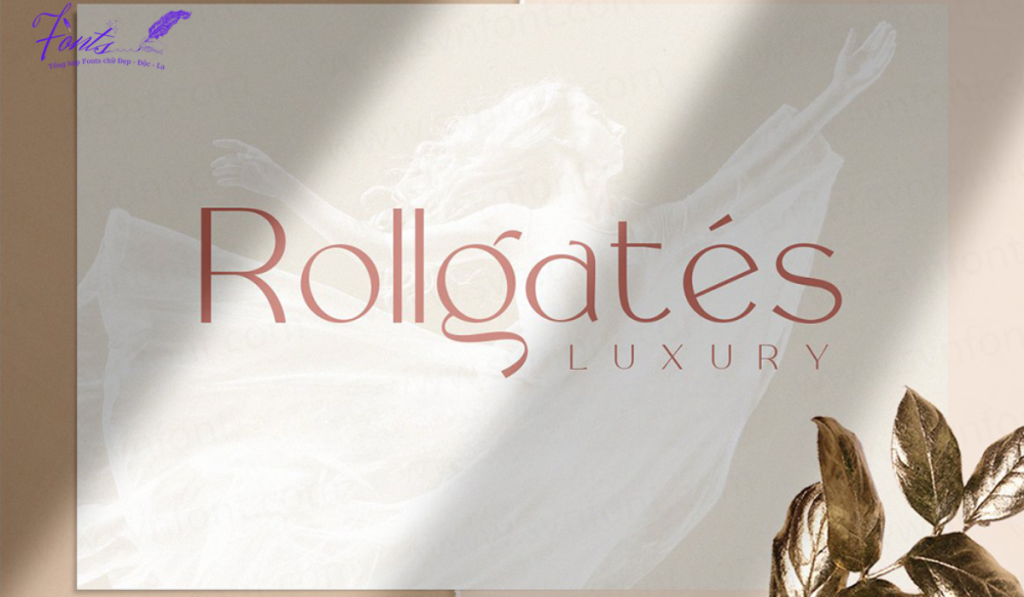
Font SVN Rollgates Luxury
Tác giả: Cotbada Studio
Bộ Font: SVN
Phân loại: Hiện đại, sang trọng
Kiểu chữ: Sans-serif
Font SVN Rollgates Luxury thuộc bộ font SVN là kiểu chữ không chân mang vẻ đẹp sang trọng và tinh tế.